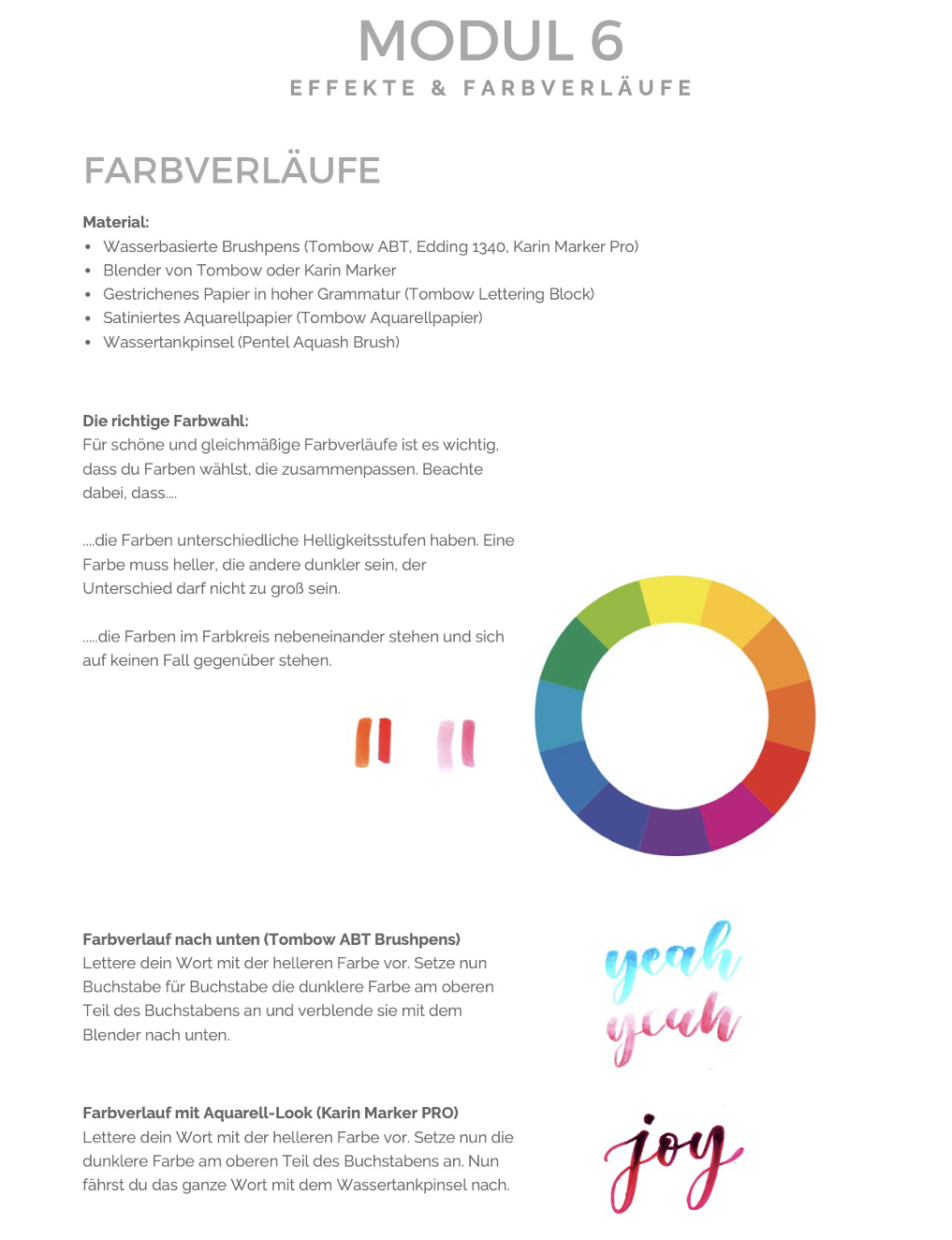
In diesem Materialpaket findet ihr Materiallisten, Erklärungen zu den verschiedenen Schriftarten von der Druckschrift über die Fake Kalligraphie bis zum Brush Lettering mit dem kleinen und dem großen Prushpen. Außerdem gibt es Übungsseiten zum Thema Blending und farbige Gestaltung von Buchstaben, kreativen Alphabeten und Schmuckelementen.
Das Materialpaket eignet sich perfekt für eine Handlettering AG, den Einsatz im Kunstunterricht, für Projekttage oder Projektwochen. Die erlernten Schriftarten können anschließend in Projekten, wie z.B. Kartengestaltung, Fenstergestaltung (mit Edding Glasmalern), Postergestaltung etc. eingesetzt werden.